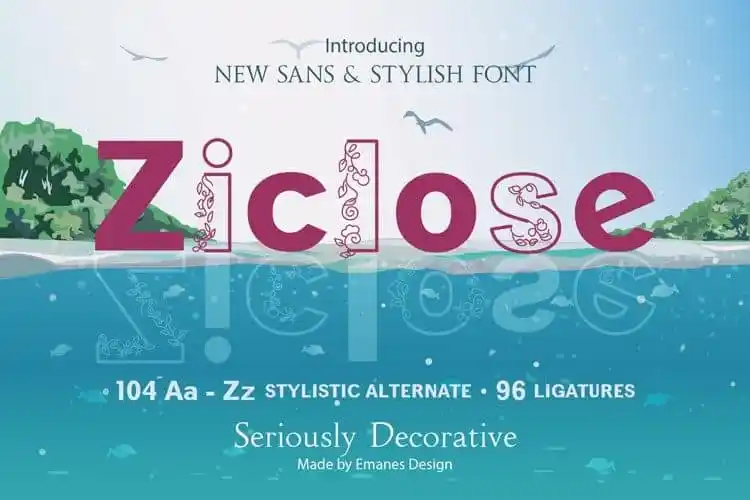
Ziclose Sans Serif Font – Download Grátis
Ziclose Sans Serif é uma fonte sans serif que traz um estilo moderno e distintivo, concebida pelo talentoso font designer emanesdsign. Essa fonte não tem canto e apresenta elementos florais e floraísticos, o que a torna única e perfeita para ambientes digitais contemporâneos. Repleta de uma diversidade de estilos únicos, Ziclose ofertará aos designers um leque de opções para sua próxima criação. Conta com três diferentes versões: Floral, Inline e Regular/Medium. Essas variantes apresentam um forte contraste que pode ser explorado, desde a letra regular até o estilo floral decorativo. Escolha Ziclose como seu próximo projeto se encaixar naquela necessidade de uma fonte sans serif com personalidade. Seja para um site corporativo ou uma publicação online, sua aparência moderna e distintiva certamente brilhará em qualquer aplicação visual. Descubra agora a Ziclose Sans Serif Font, projetada para se destacar no ambiente digital contemporâneo!